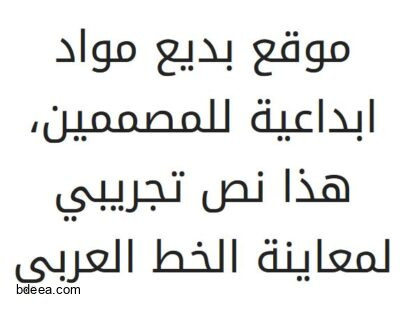
تحميل خط صلاح الجديد العربي المميز للمصممين Salah otf arabic font download يضيف لمسة فنية رائعة الى التصاميم العربية والمطبوعات والعروض التقديمية بالكلمات العربية والارقام بشكل مميز يمكنك تثبيته على جهازك والبدء باستخدامه في برامج التصميم
يتميز بالخط بالمرونة والخفة والشكل الانيق في الكتابة والحروف يمكن معاينته وتجربة استخدامه ليضيف لك تميز الى تصاميمك